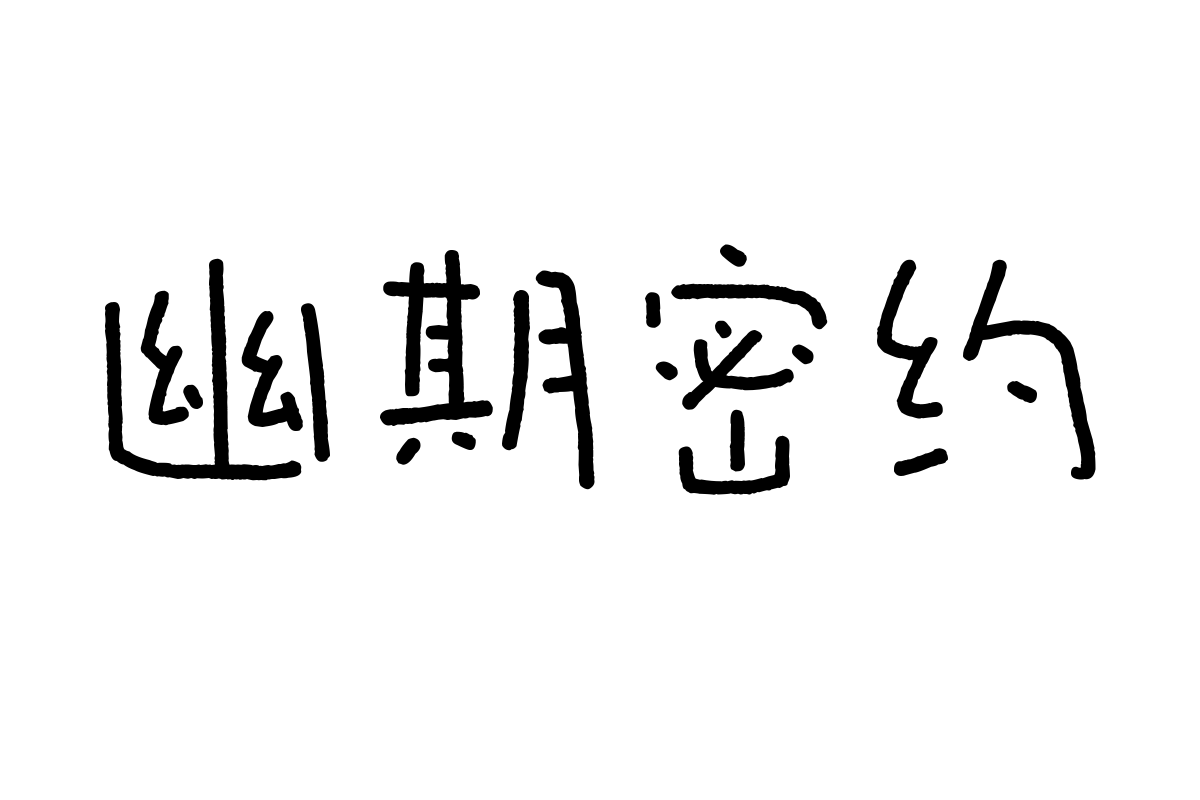
**龚帆悦心体系列由龚帆设计制作,包含细、中、粗三个字体。该系列字体稚气未脱又兼具可爱的手写艺术字体,字体舒展大方,观赏度更强**。
龚帆悦心体系列是龚帆字库出品的一款个性化字体,最新版本中的字符共6925个,适用于影视游戏字幕、现代诗歌、短文等场景。该字体的设计理念旨在提供一种既有个性又不失美观的书写体验。其特点包括稚气未脱的可爱风格和舒展大方的字体形态,使其在视觉上更具吸引力。